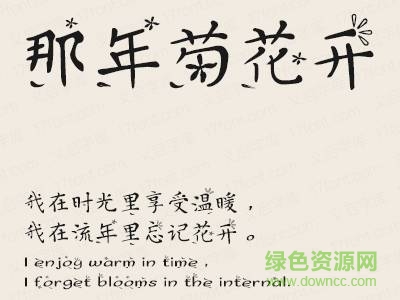
義啟那年菊花開(kāi)字體
義啟那年菊花開(kāi)體是一款義啟出品的重陽(yáng)節(jié)字體,自帶花形,富有韻味,讓大家感嘆離殤。字形優(yōu)雅適合藝術(shù)創(chuàng)作、噴涂等。歡迎大家來(lái)綠色資源網(wǎng)踴躍下載義啟字體!
義啟那年菊花開(kāi)體
義啟那年菊花開(kāi),那年重陽(yáng), 迎著明媚的陽(yáng)光, 窗外的菊花花開(kāi)正艷, 是誰(shuí),在譜寫(xiě)離別的篇章?我剪一段時(shí)光裹住心傷。